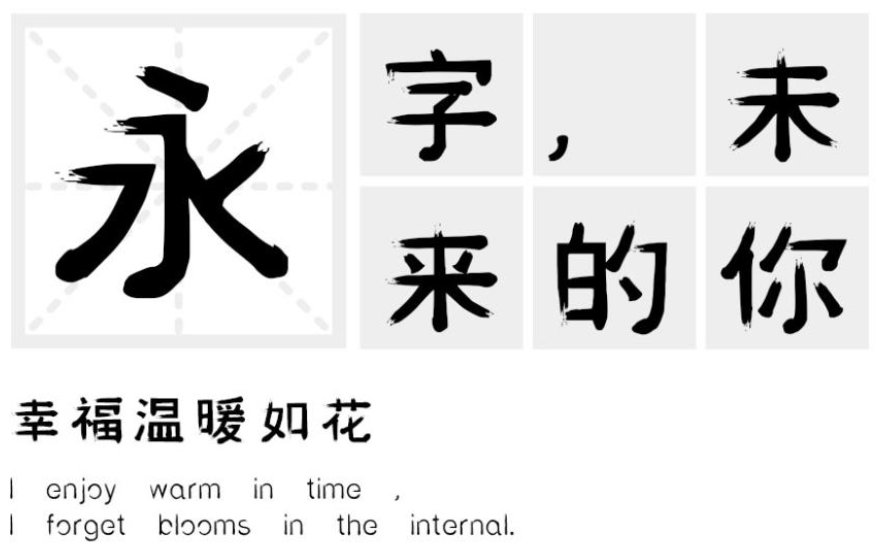
汉标颓废体发布
字体名称:汉标颓废体
字体类别: 创意字体
适用场景:广告、影视、海报、文艺书刊
汉标颓废体简介:汉标颓废体字体是一款适合大标题艺术和广告的艺术字体;该款字体采用大量带有飞白的笔画,以及夸张的横、撇、捺,去表现少年,桀骜不驯、永不服输的个性特点,以及运用带有弧线的笔画去表现少年随性、不羁的一面。适用于文艺类的书刊、品牌广告和产品包装设计,以及社交网络的个性化用字。
汉标颓废体预览图展示: